ATypI 2019 TOKYOでの講演「江戸時代と現代の極太書体」
2019年9月4日からの4日間、東京の日本科学未来館で「ATypI 2019 TOKYO」が開催されました。ATypI(エイタイプアイ)は、タイプコミュニティとビジネスのためのグローバルフォーラムで、毎年、世界の選ばれた都市でカンファレンスを開催してています。
63回目となる「ATypI 2019 TOKYO」のテーマは、「Rediscover ― 変化と伝統の都市、東京でタイポグラフィを再発見しよう!」。ワークショップと講演セッションでは、世界各国から講師・スピーカーを迎え、タイプデザインの歴史や文化、画期的なタイポグラフィ、デジタルフォントにおける最新のテクノロジーなどの発表が行われました。
タイププロジェクトの和文担当デザイナー・石川とも子は、「江戸時代と現代の極太書体」と題した講演で、勘亭流、相撲字、籠字(かごじ)、そしてデジタルフォント時代の極太書体の特徴と事例について語りました。以下、その一部をご紹介します。
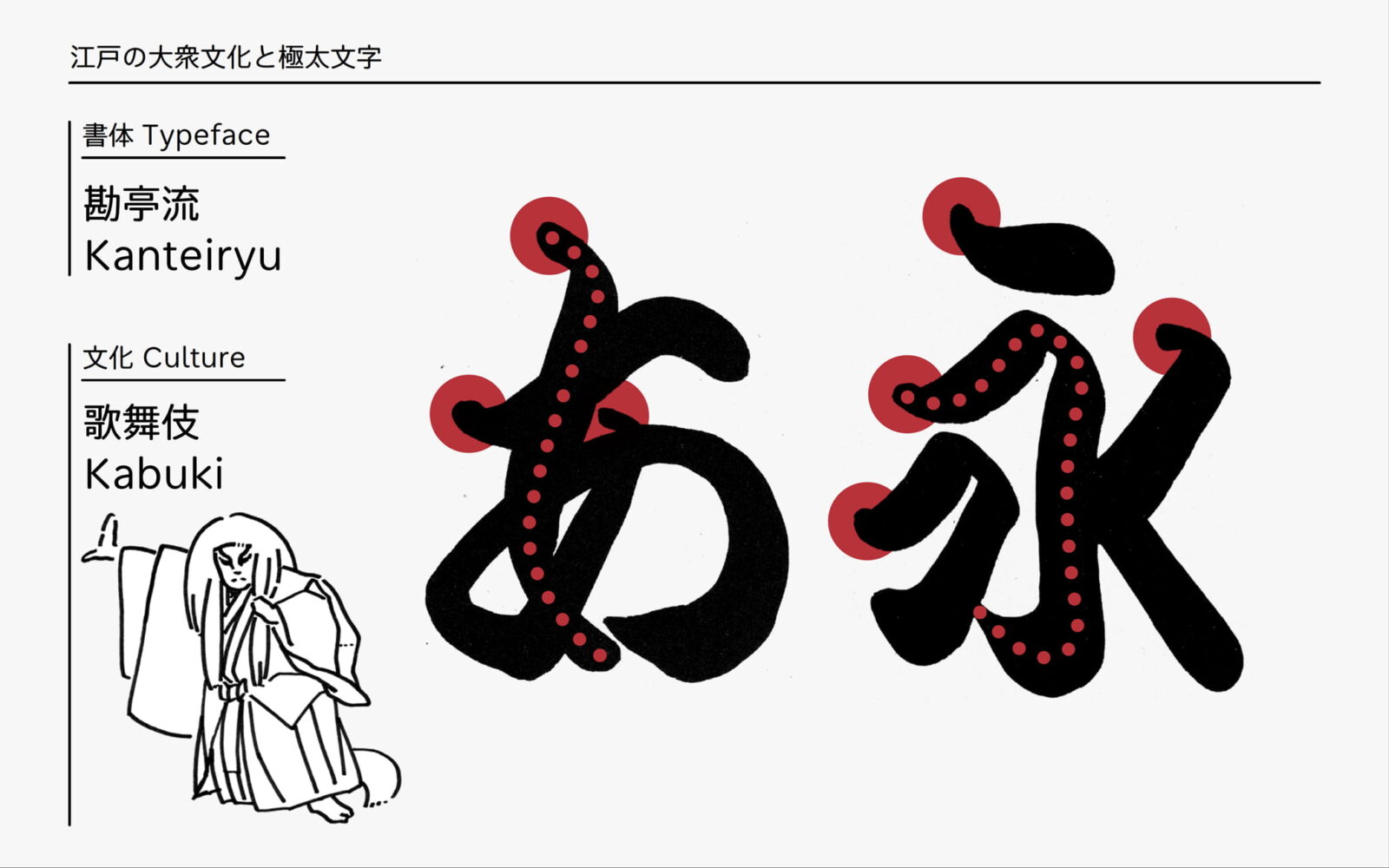
「日本では長らく戦乱の世が続いていたのですが、江戸時代の265年間は、社会が安定して様々な文化活動が活性化します。大衆の間にも娯楽や読み書きが広まりました。歌舞伎や相撲といった大衆芸能が発達し、それと共にある広告や看板に施される文字にも趣向が凝らされるようになります。そうして歌舞伎なら勘亭流、相撲なら相撲字、といった専用書体が登場しました」
「勘亭流は太い筆に濃い墨をどっぷりつけて書きます。くねっと曲がる起筆、うねりのある骨格が特徴です」
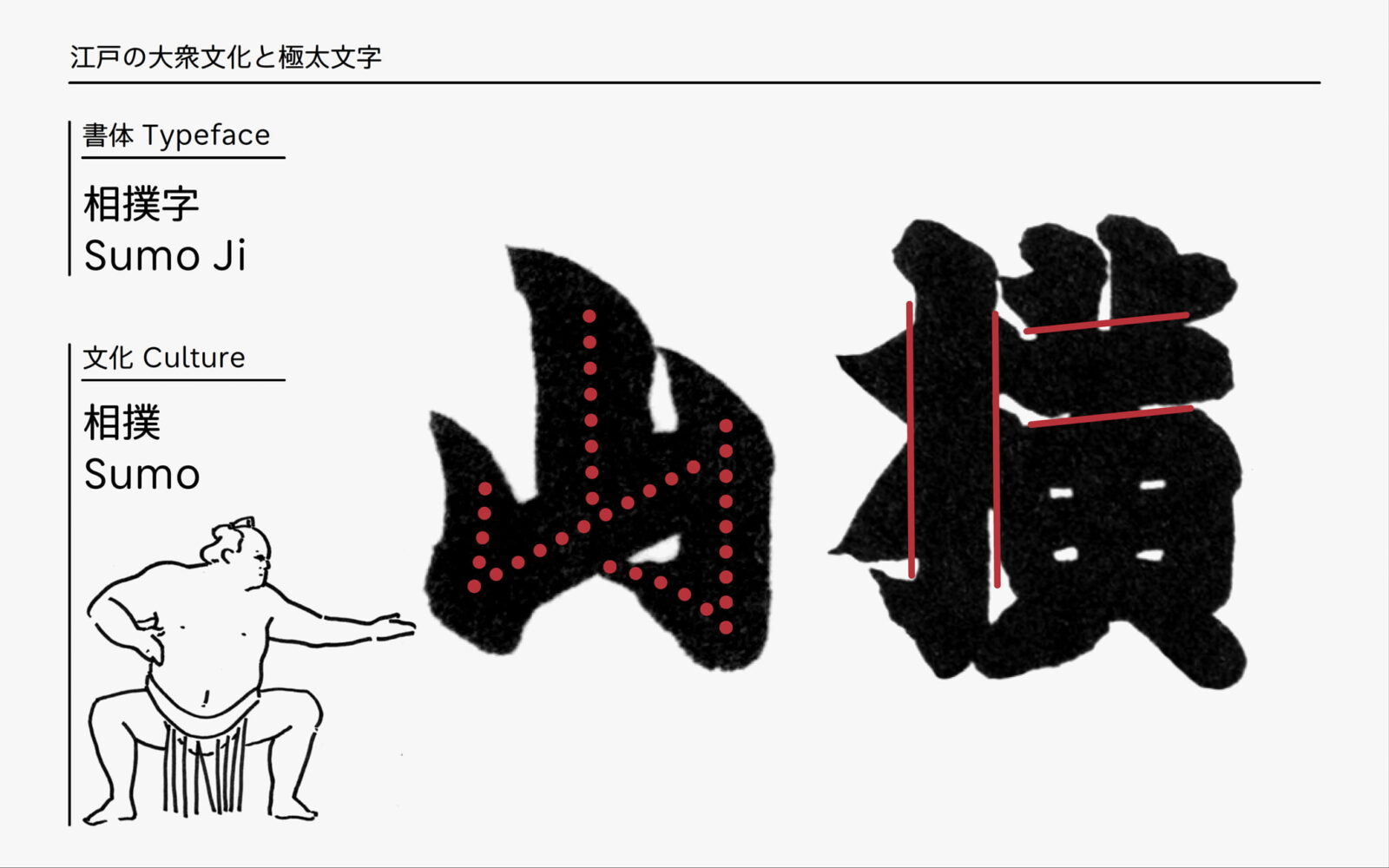
「相撲字は逆に直線的な骨格をしています。筆画は抑揚を付けずに太くどっしりと書かれます。巨体の力士がぶつかり合う、力強いスポーツである相撲の性格が文字にも現れています」
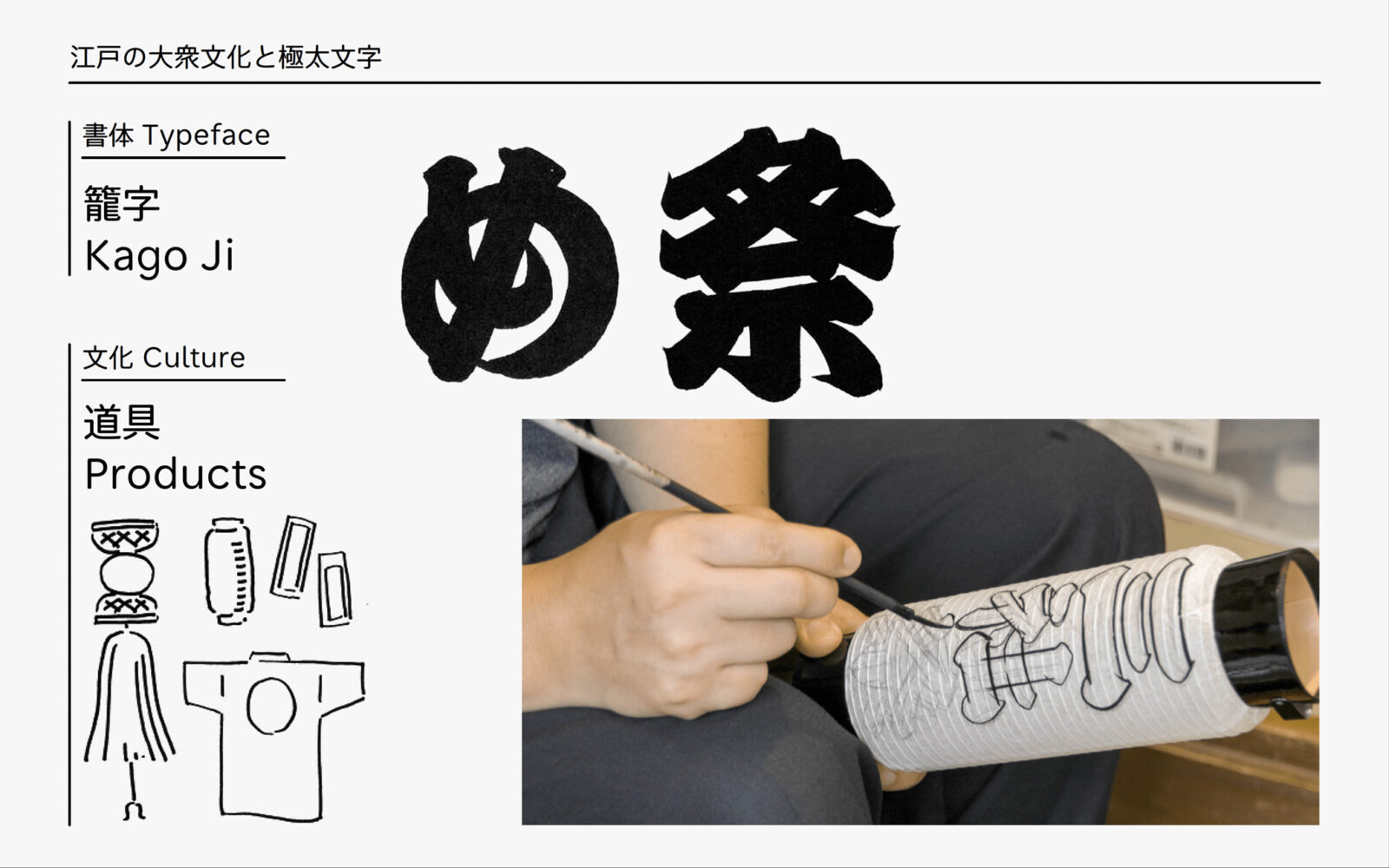
「籠字は勘亭流や相撲字とすこし性格の違う書体で、特定の文化の専用書体として始まったものではありません。看板、千社札、半纏など、文字を目立たせたい場面でよく使われます。細い筆で輪郭をとってから中を塗りつぶす、という方法で書くのが籠字です」
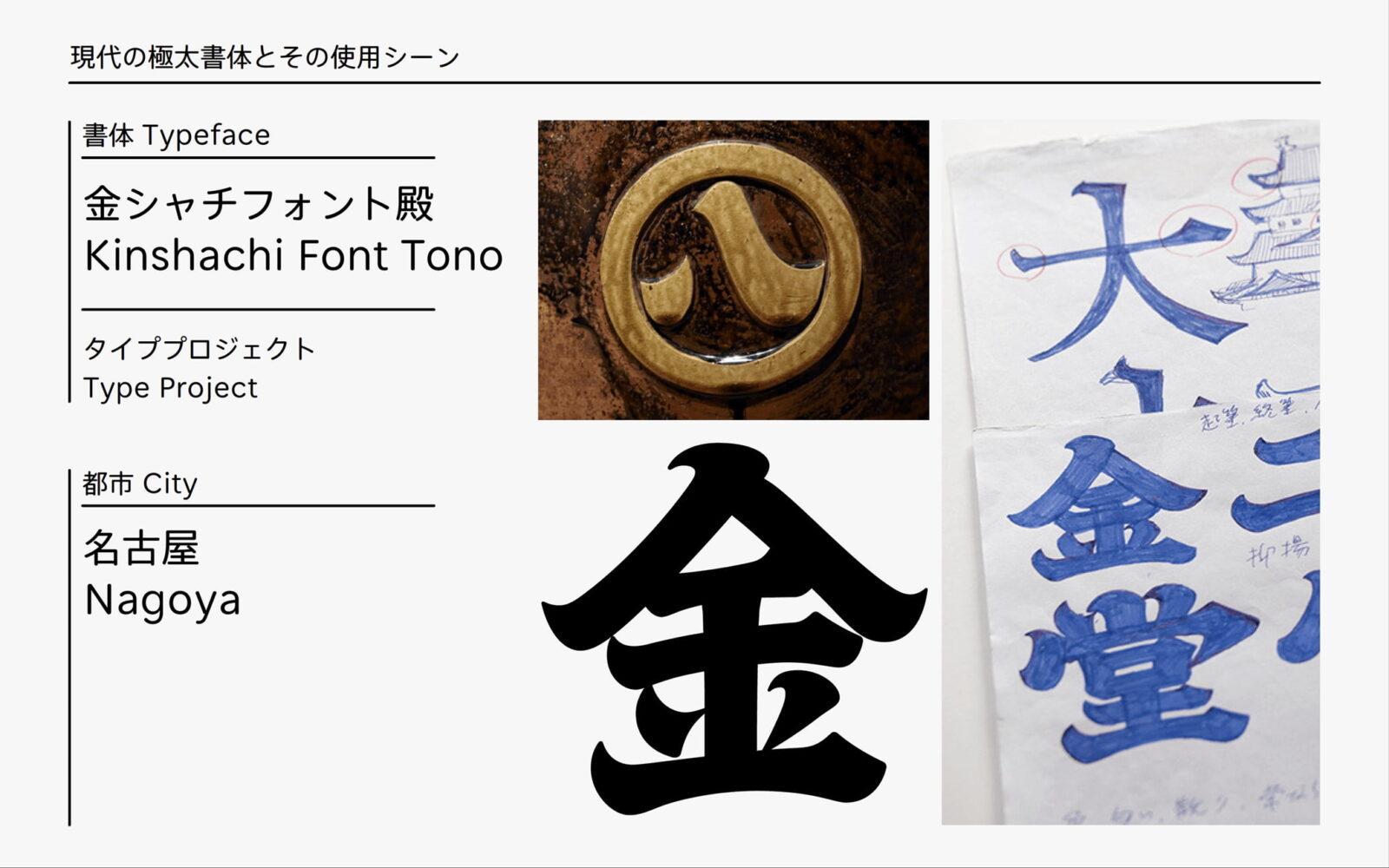
「最後にご紹介するのは金シャチフォント殿です。金シャチフォントは、タイププロジェクトが立ち上げた都市フォントプロジェクトのひとつとして、名古屋をイメージするフォントをつくり、地元で育て世界へ発信しようという試みで現在開発しています」
「名古屋で古くから親しまれている市章、丸八マークの筆法を応用して文字を描きました。文字の太さは、味噌カツ、土手煮といった名古屋メシのこってり濃いめの味付けにも由来しています」
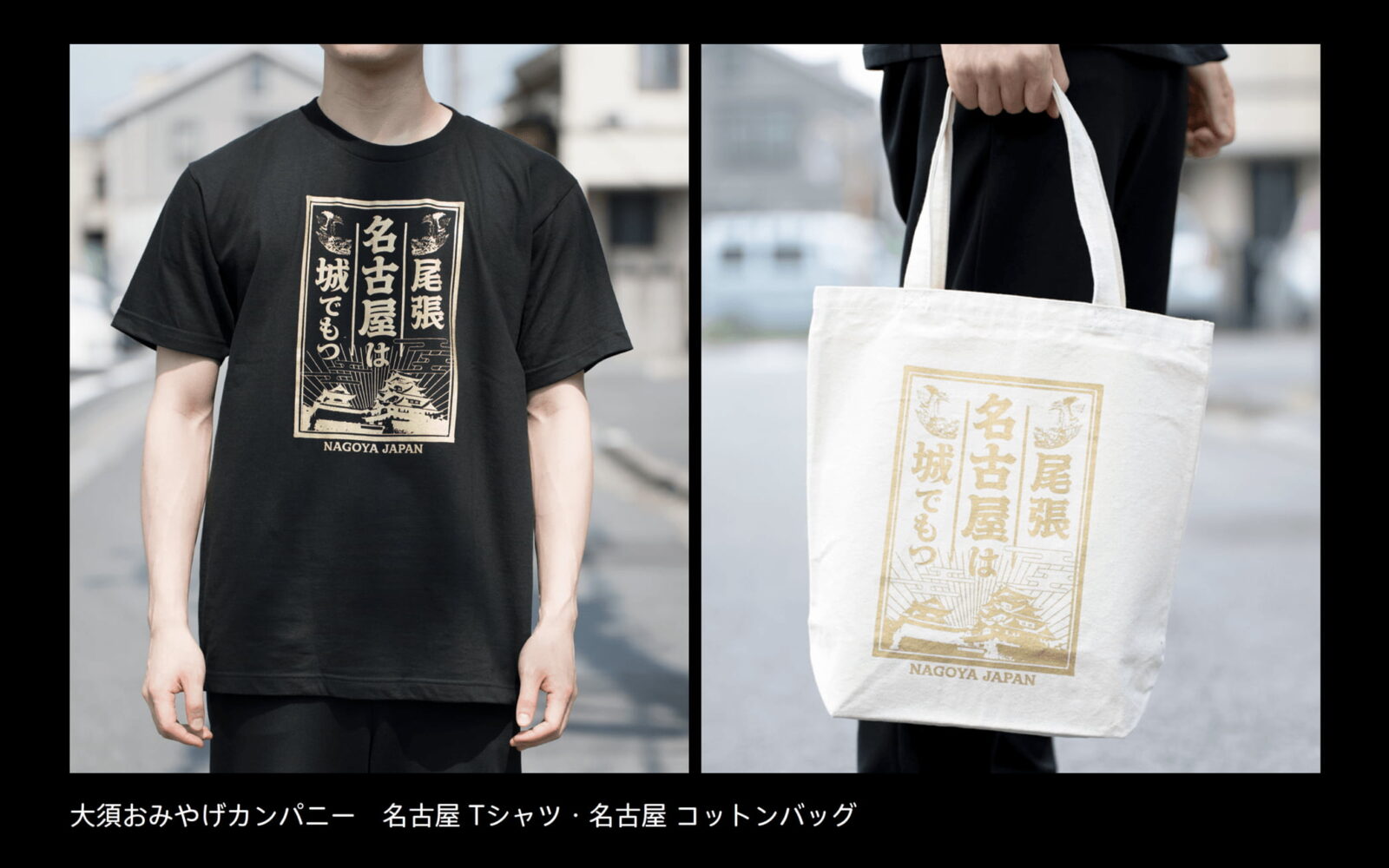
「金シャチフォント殿を使用したお土産が現在名古屋で販売されています(http://osu-omiyage.jp)。いま私が着ているのも金シャチフォントTシャツです。文字メインのグラフィックですが、名古屋の印象を持った太身の文字を使用することで、名古屋らしさのあるご当地グッズに仕上がっています」
「タイププロジェクトでは、この金シャチフォントをリリースするため開発を進めています。今後の展開もお楽しみに」